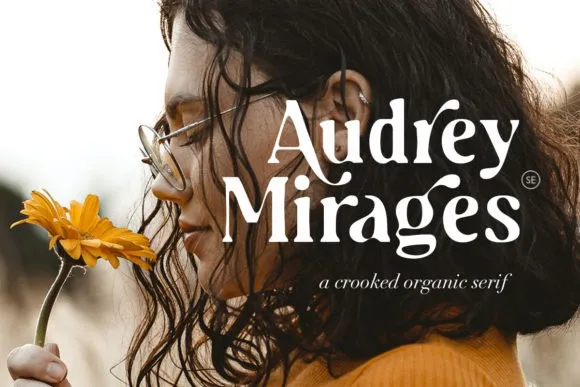
A Audrey Mirages Font é uma elegante tipografia serif desenvolvida especificamente para títulos e headlines. Ideal para designers que buscam uma opção moderna e clássica, esta fonte foi criada pela saridezra no site 99designs e está disponível para uso de forma gratuita. Suas linhas afiadas proporcionam um brilho único que torna qualquer projeto mais chamativo. Seja para editoriais, design gráfico ou qualquer outro tipo de projeto onde você deseje destacar sua mensagem, esta fonte é uma escolha perfeita. Com apenas alguns cliques e um toque da nossa mão criativa, ela dará vida à sua ideia e a tornará ainda mais memorável e impressionante. Experimente Audrey Mirages Font agora e veja como ela pode transformar o seu design em algo realmente especial.